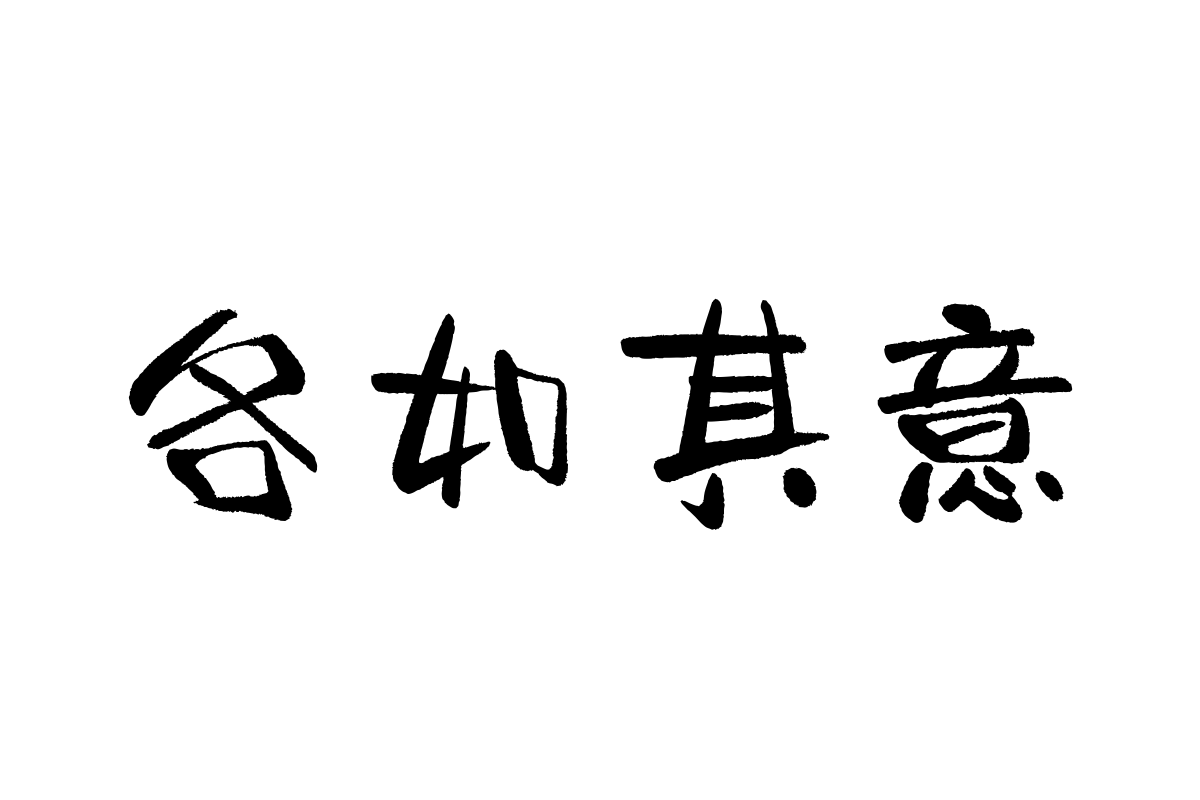
汉仪二码墨书是一款具有独特风格的书法字体,以其流畅的笔画和独特的结构设计而闻名。这款字体采用了传统的书法风格,结合了现代的设计元素,使其既保留了传统书法的韵味,又不失现代感。
在笔画上,汉仪二码墨书注重线条的流畅性和力度的控制,使得每个字都显得饱满而有力量。同时,它的笔画结构也较为复杂,既有直线也有曲线,使得整个字体看起来既有层次感又有动感。
在结构上,汉仪二码墨书采用了一种独特的布局方式,使得每个字都显得紧凑而有力。这种布局方式不仅增加了字体的美感,也使得整个字体看起来更加协调和统一。
总的来说,汉仪二码墨书是一款非常独特且富有个性的书法字体,无论是用于打印还是用于设计,都能展现出其独特的魅力。